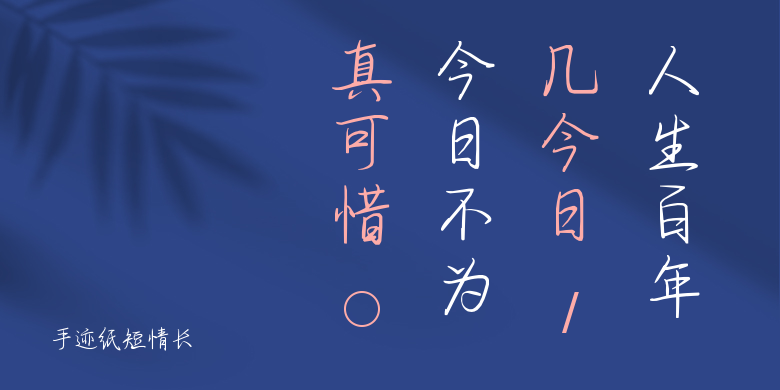
手迹纸短情长
手迹纸短情长,这款字体结构工整、笔画清晰,兼顾美观与易读性,适用于标题、正文、海报、包装、LOGO 等多种场景。字形优雅稳定,风格百搭耐看,适配日常排版与创意设计,让文字呈现更舒适、更具质感。手迹纸短情长一笔一画,皆是细节,以均衡的比例、流畅的线条打造舒适视觉体验,字形端正大气,风格简约现代。无论是商业设计、品牌宣传还是日常排版,都能轻松驾驭,让文字更有格调与力量。手迹纸短情长字体下载。